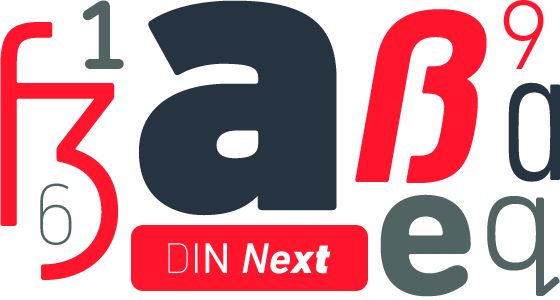
Textschrift zu FF DIN
ich habe auch schon 6 seitige flyer aus der din condensed gesetzt, lesbar ist das schon,
wenn auch nicht schön auf dauer.
mischen mit ähnlichen grotesk-schriften würde ich sie aber nicht. entweder mit 'ner serif
die character hat oder innerhalb der din (da kann man auch einiges rausholen)
das hochgelobte ß ist wohl nur als alternate-zeichen verfügbar? das @ hätte ich auch gern zweistöckig als alternate, ähnlich wie das bei der interstate der fall ist. und wenn schon alternates, dann bitte auch runde i-punkte, die hat die FF Din und die finde ich harmonischer.
bei der bold gehe ich mal davon aus das du dich bei der überschrift verschrieben hast ;)
Ach Mensch - ja, verschrieben ... sorry.
Ich hab kein ß auf der Tastatur oder was meinst Du mit Alternates? Ich habe die Zeichen nicht wirklich in der Reihenfolge getippt.
ich habe auch schon 6 seitige flyer aus der din condensed gesetzt, lesbar ist das schon, wenn auch nicht schön auf dauer.
Ja, die Condensed nehme ich teilweise für Text, aber nicht die Regular.
linotype schreibt davon:
"Das alternative ß wirkt wie eine Kombination aus einem langen s und einem langen z. Diese historische Buchstabenform wird auf Straßenschildern in Westberlin benutzt."
Ihr habt ja recht. Da es aber wohl eher keine umfangreichen gedruckten Schriftwerke geben wird, werde ich in einem Entwurf konsequent die DIN einsetzen, und parallel eine Version mit Antiqua verfolgen und diese gegebenenfalls vorstellen. Gut schaut's ja aus und die Kunden haben oft ein erstaunlich gutes Gefühl dafür, was zu ihnen passt und was nicht, wenn es vor ihnen liegt ... (vielleicht gibt es ja Überraschungen ). Im Web werde ich um Arial/Times/Courier nicht rumkommen. Courier geht gar nicht. Muss ich alles mal ausprobieren.